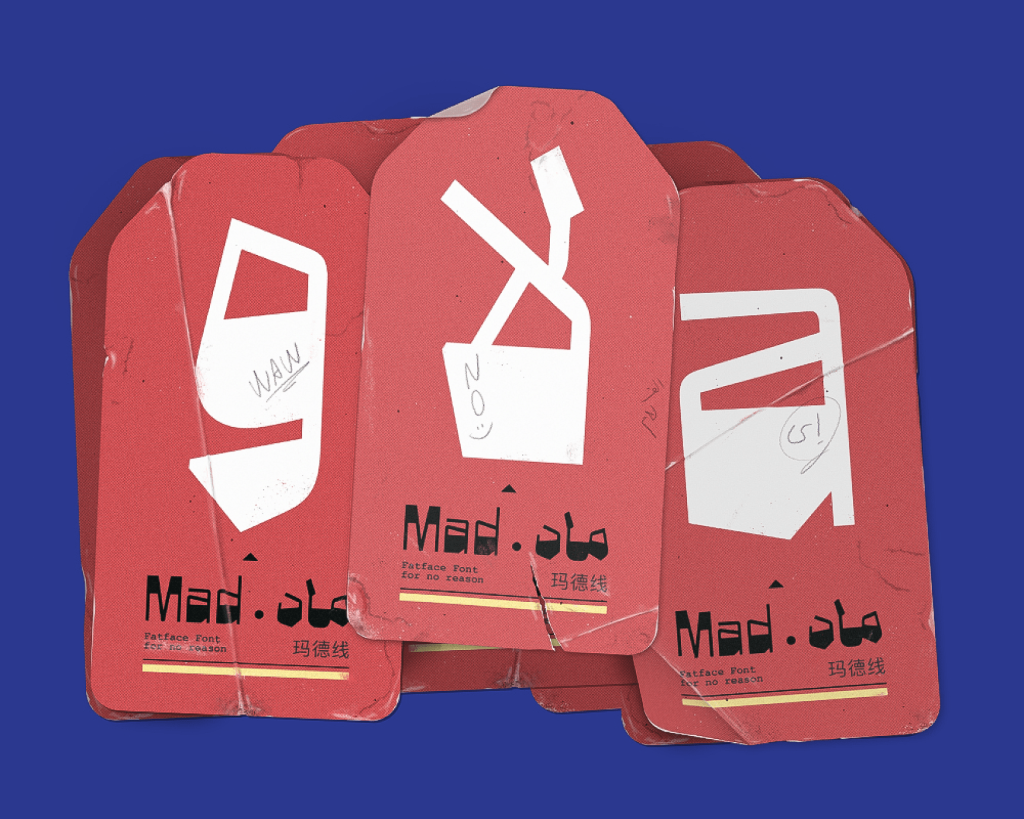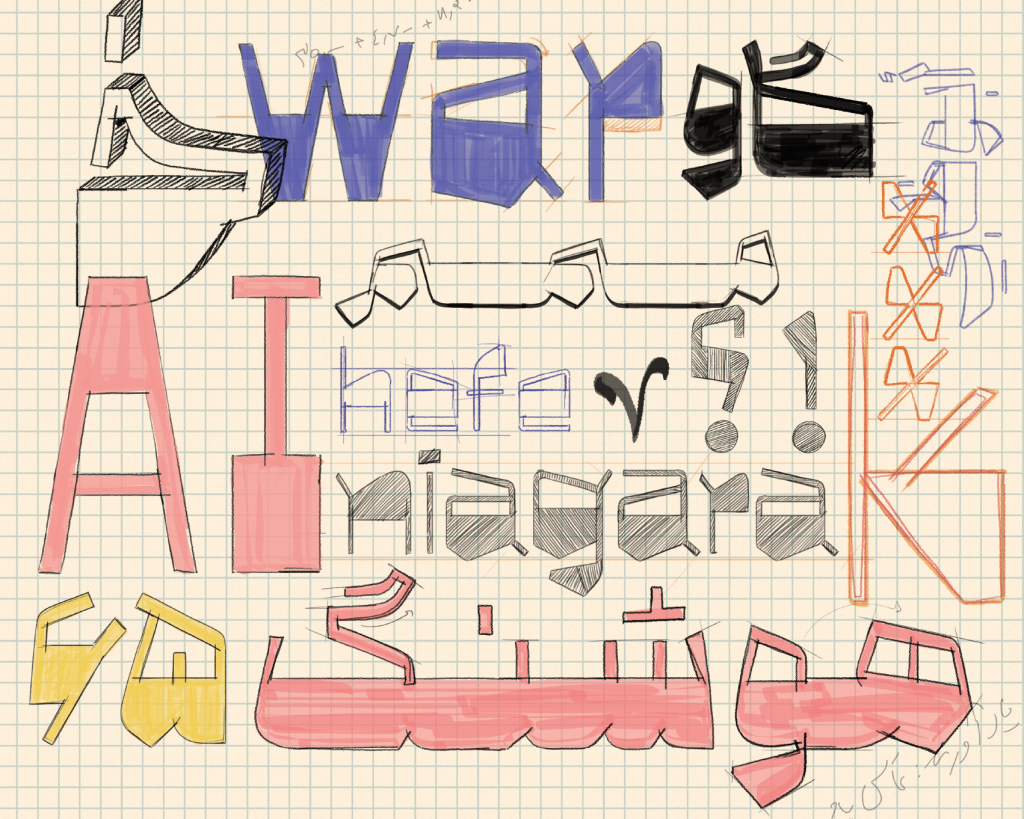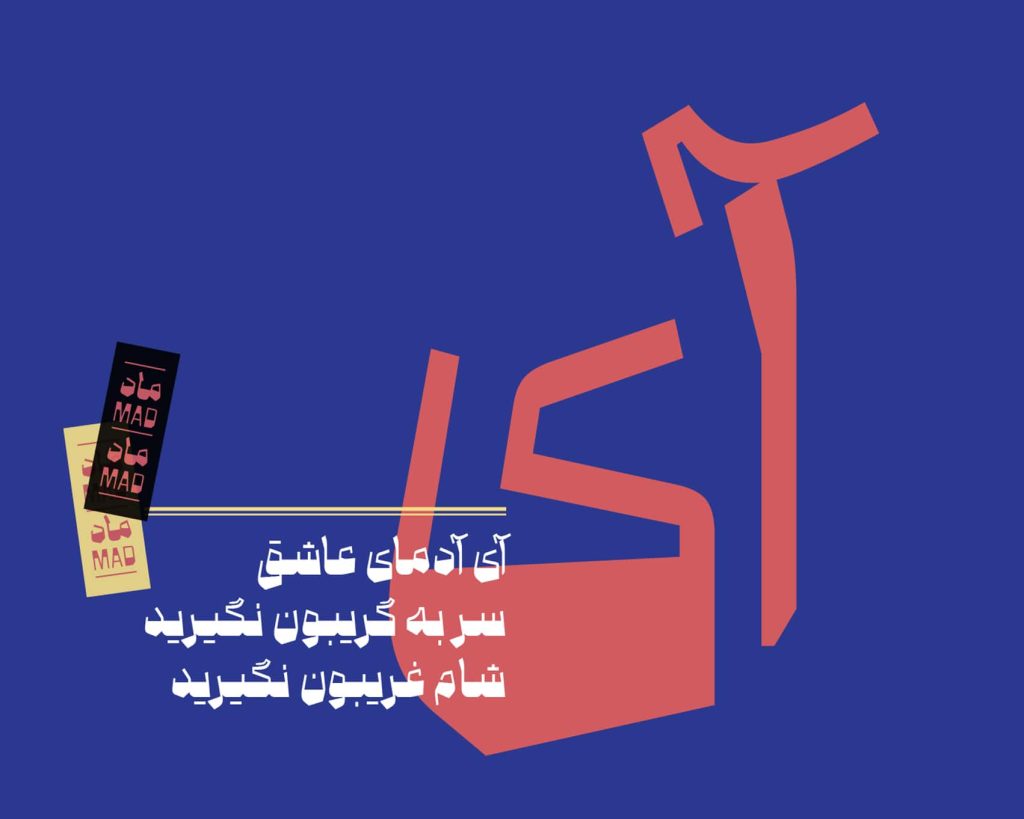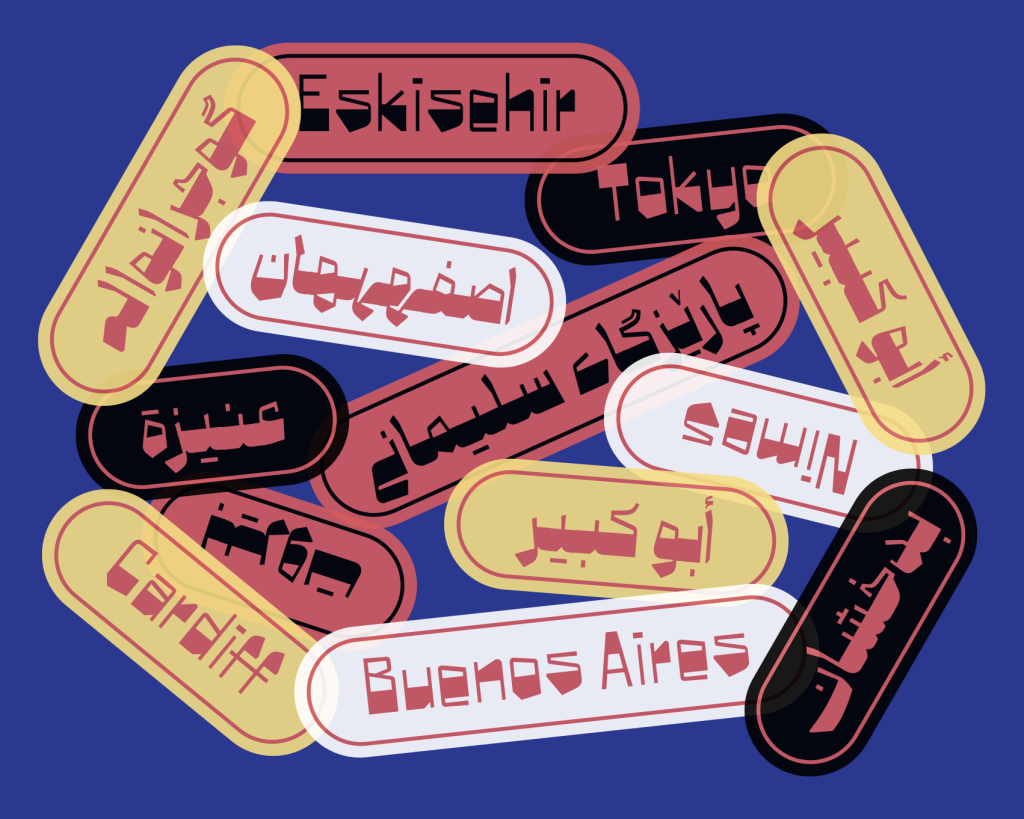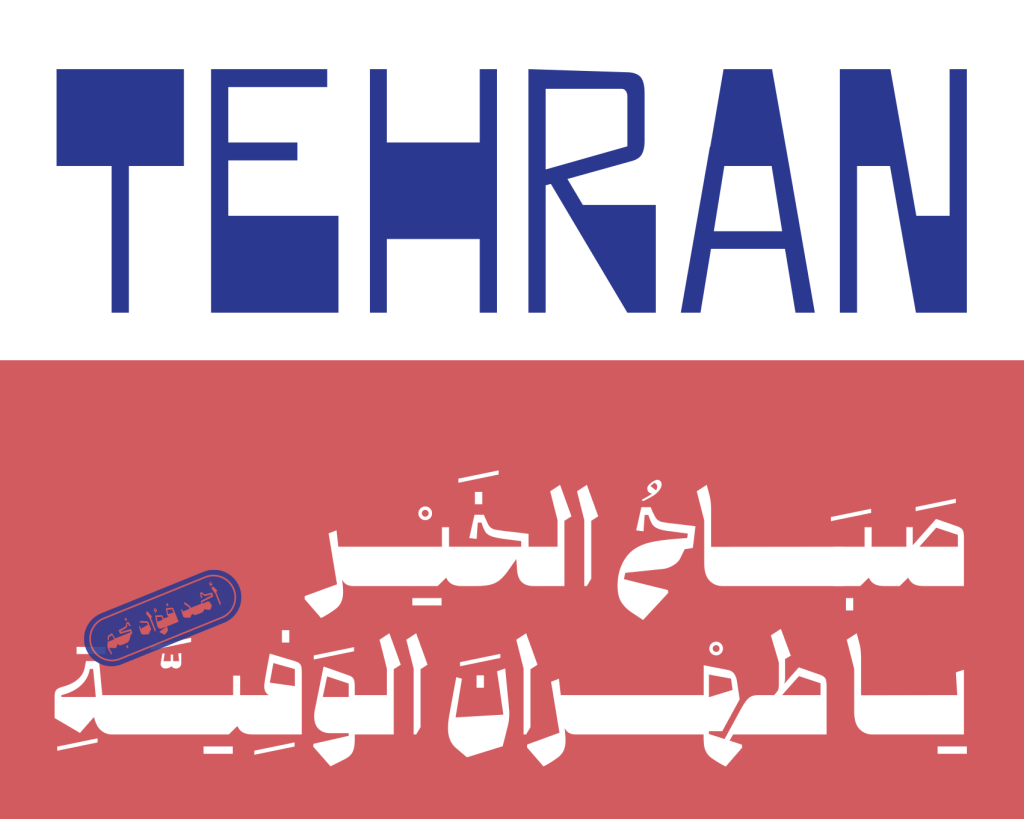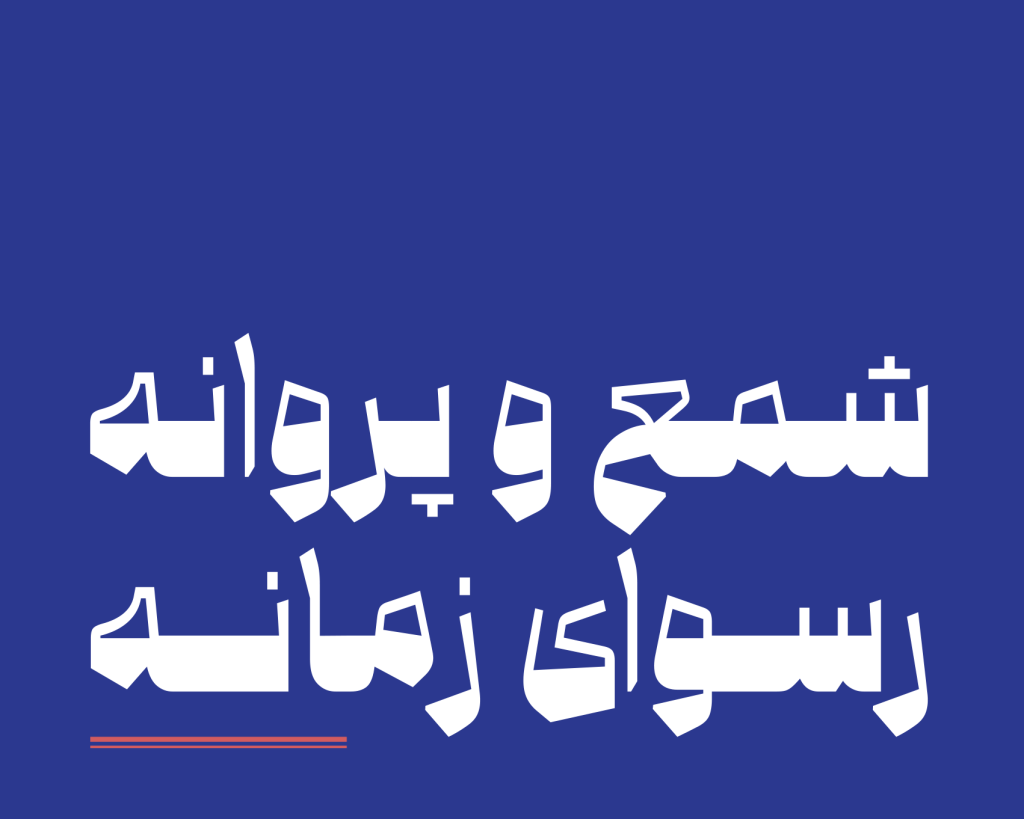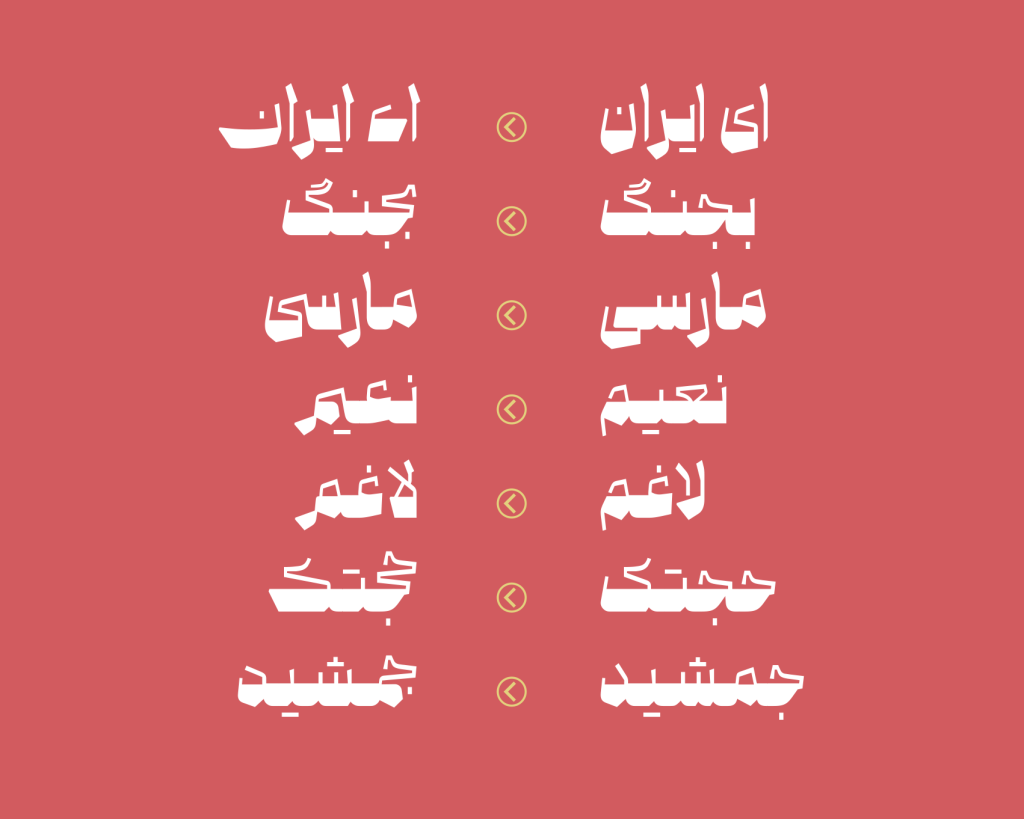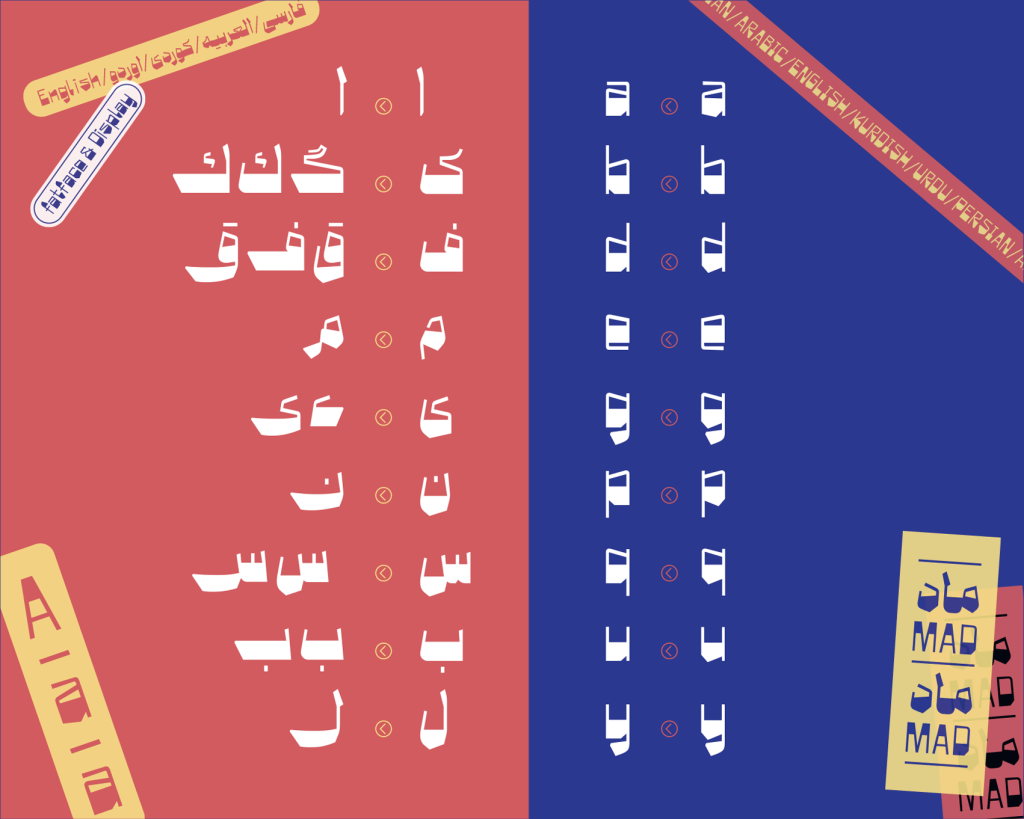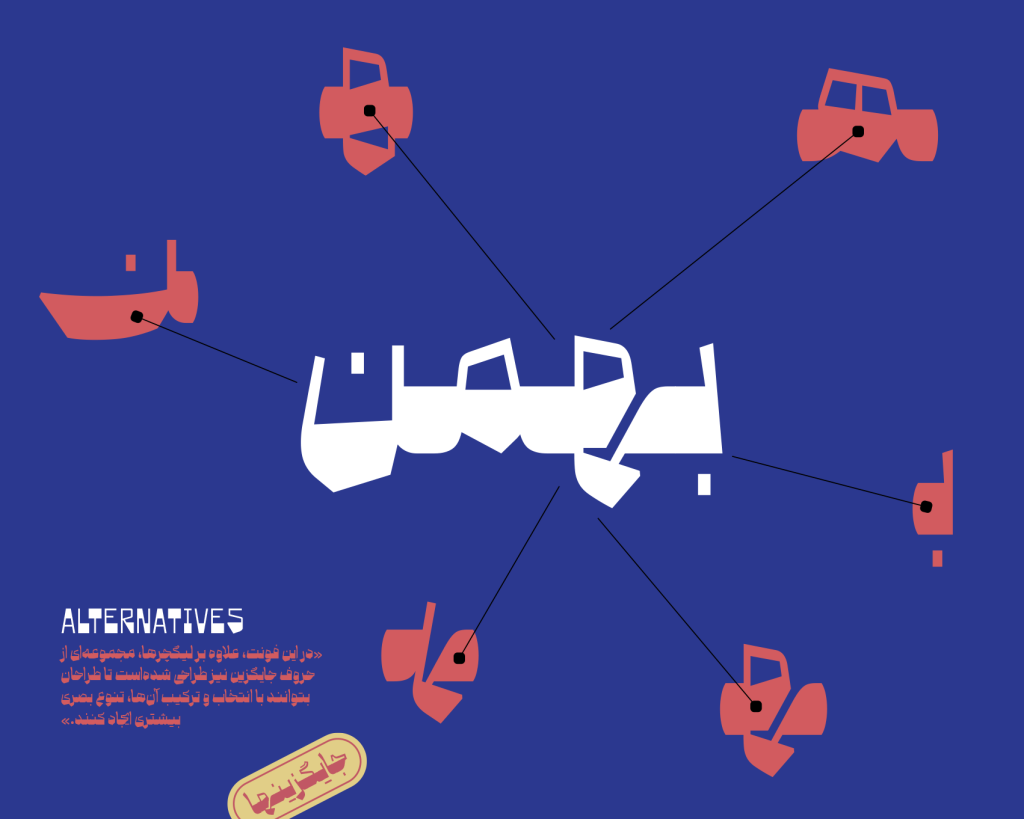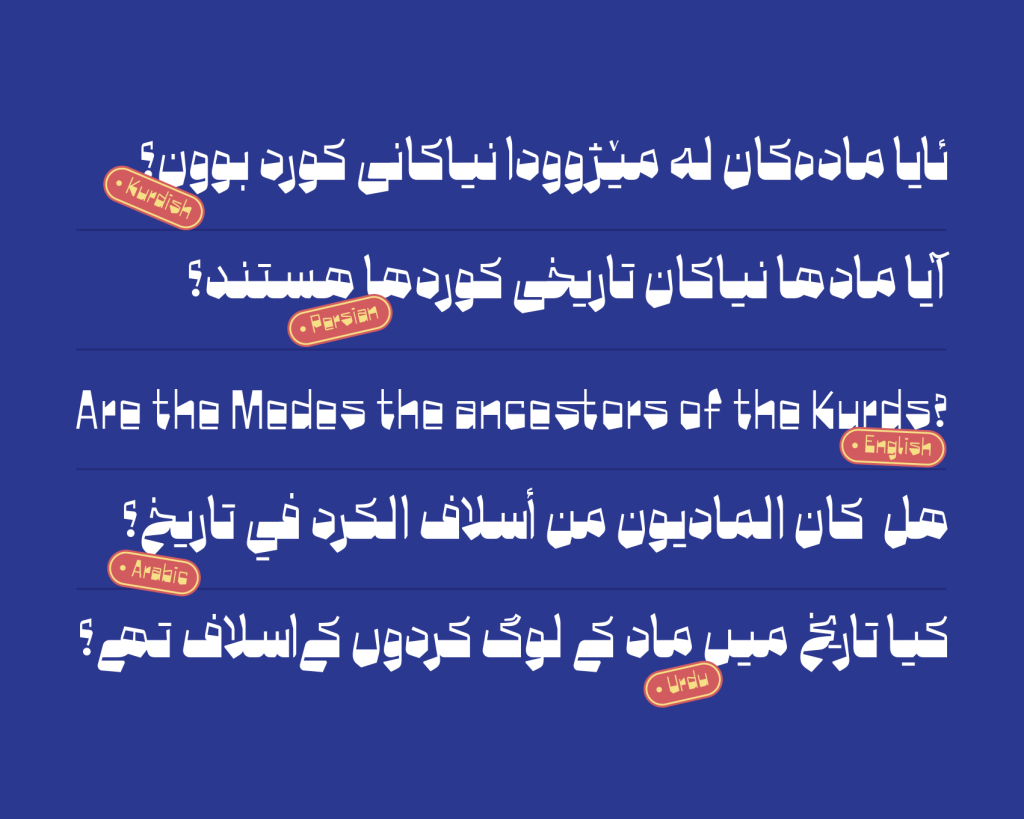
فونت ماد قلمی مناسب عناوین وتیتر ها با پشتیبانی از زبان ها و ترکیبات مختلف است . با ما همراه باشید تا این تایپ فیس زیبا را به شما معرفی کنیم.
فونت ماد – قلمی با کنتراست بالا
ماد قلمی مناسب عناوین تیتر ها و … می باشد و اصولا برای متون ریز و بلند طراحی نشده است. نمایشی؛ سنگین، تند وتیز است از هندسه ساده ای استفاده می کند . با دقت در ساختار طراحی آن متوجه کنتراست بسیار زیاد این قلم می شویم و سادگی ساختار، ترکیبی تازه از خوانایی و ویژگی‌های بصری نوآورانه ایجاد می‌کند؛ فونتی که در عین سادگی، نگاه مخاطب را با تصویر متفاوت خود درگیر می‌کند .
پس در یک کلام میشه گفت هندسه‌ی ساده‌ و امکانات نمایشی، ماد رو تبدیل به فونتی مناسب برای عنوان و تیتر کرده است
پشتیبانی تایپ فیس ماد از زبان های مختلف
تایپ فیس ماد از زبان های بسیاری پشتیبانی می کند از جمله این زبان ها می توان به زبان های فارسی عربی،انگلیسی اردو کردی و … اشاره نمود ، همچنین ترکیبات و کاراکترهای جایگزین متعدد، قابلیت‌های کاربردی گسترده‌ای در اختیار طراح قرار می‌دهد
ماد در کاربردهای مختلف انعطاف‌پذیری بالایی دارد در صورتی که در ظاهر تیز و شارپ و قدرتمند به نظر می آید، و می‌تواند در موقعیت‌های متنوع عملکرد خوبی ارائه دهد. کنتراست شدید در کنار «چشم‌های بزرگ», که نقش مهمی در افزایش خوانایی دارند,  که سبب کاربرد «ماد» برای نمایش انواع عناوین و تیترها شده است.
در ذیل تصاویری زیبا از این قلم را برای شما عزیزان آماده کرده ایم